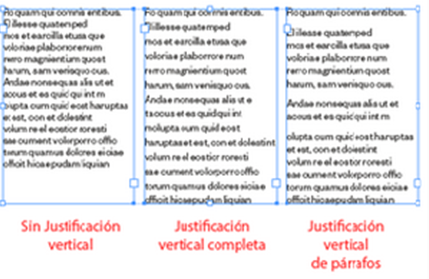
Tipografía
Veremos que es la tipografia
Tipografía
1. Fuente tipografia
1. Se define como estilo o apariencia de grupo completo de carateres, numeros y signos regidos por unas caracteristicas comunes.
1. Medidas Tipograficas
1. Letra: *Tamaño de letra
1. Linea: *Interlinea *Profundiad *Justificacion
1. Disposicion del Texto
1. Derecha Izquierda Centro Justificado
2. Estructura de la Letra
1. Asta
1. Anillos
1. Brazo
1. Cola
1. Ascendiente y Descendiente
1. Oreja Ojo y redaba
2. Arte en el cual podemosdiseñas letras y componer textos de tal manera que se pueda leer facilmente
1. Grupos de la Tipografia
1. Tipografía con Serif
1. Tipografía Sans